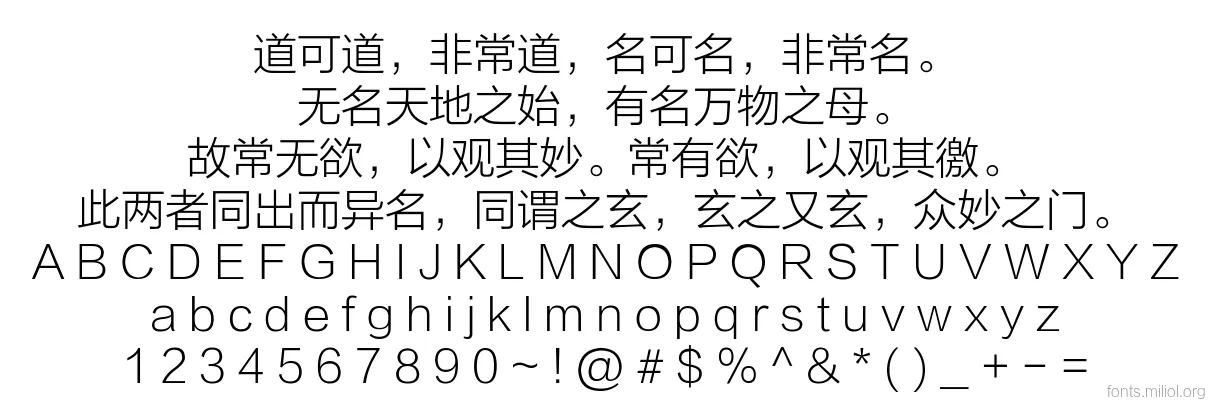
**方正兰亭纤黑_GBK字体简介**
方正兰亭纤黑_GBK(FZLanTingHei-EL-GBK)是一款由方正字库设计的中文字体,属于兰亭黑系列的纤细版本。其字形修长优雅,笔画干净利落,兼具现代感和实用性,尤其适合标题、广告、品牌设计等需要突出视觉美感的场合。作为GBK编码字体,它支持包括简体中文、繁体中文及日韩汉字在内的多种字符,兼容性广泛。
该字体以极细的线条和均匀的字重为特点,在保持清晰可读性的同时,赋予版面轻盈时尚的格调。无论是印刷品还是数字媒体,方正兰亭纤黑_GBK都能为设计增添细腻的高级感,是设计师和排版爱好者的优质选择。